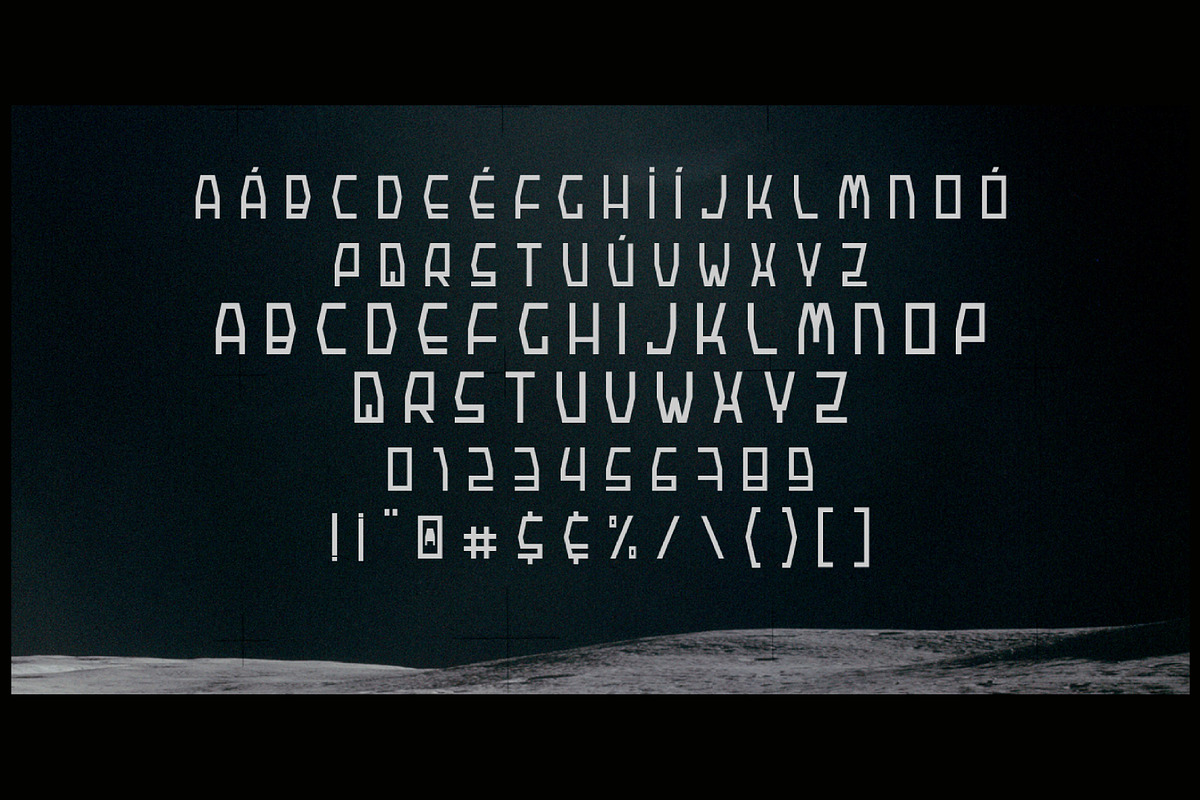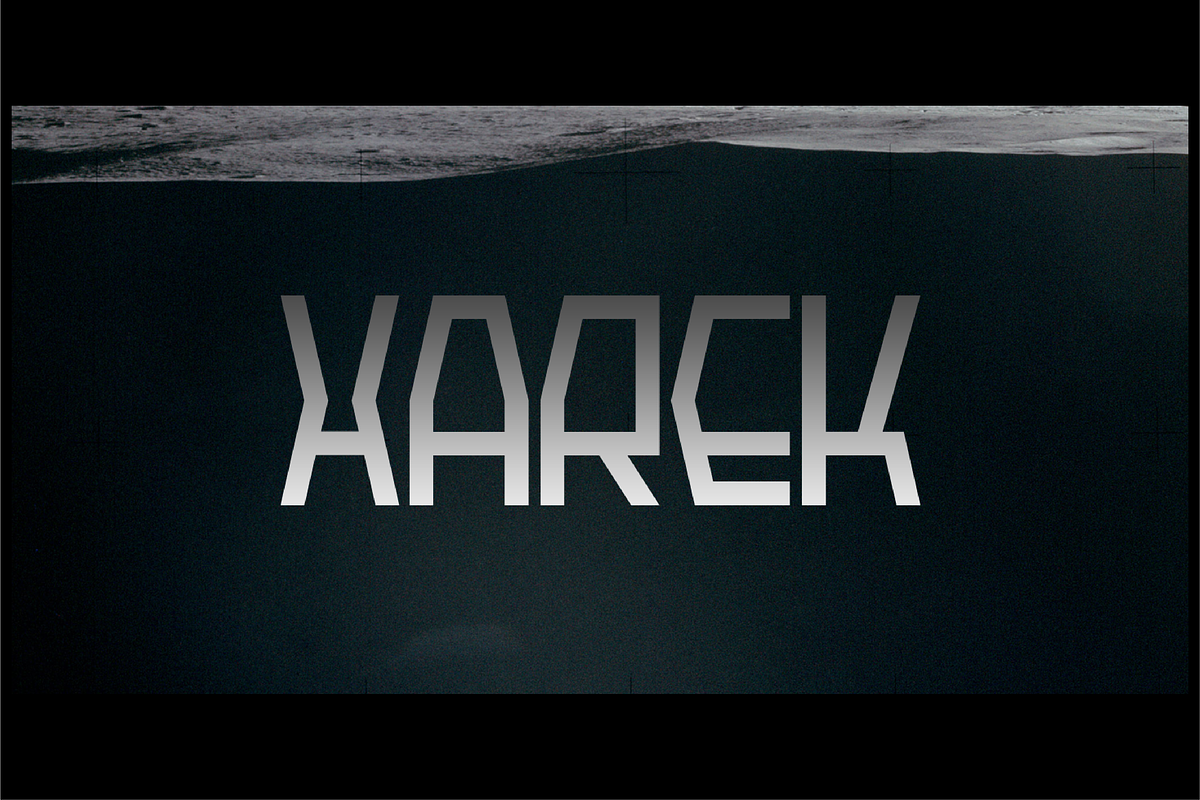
Xarek
" X A R E K " F o n t This Font contains 96 characters, including uppercase, lowercase, numbers and symbols. TTF + OTF format Registered source Tipografía Display Contemporánea. Una fuente geométrica con caracteres únicos y un estilo visual disruptivo. Perfecta para branding de tecnología, posters de ciencia ficción o proyectos editoriales que requieren una identidad fuerte y moderna.